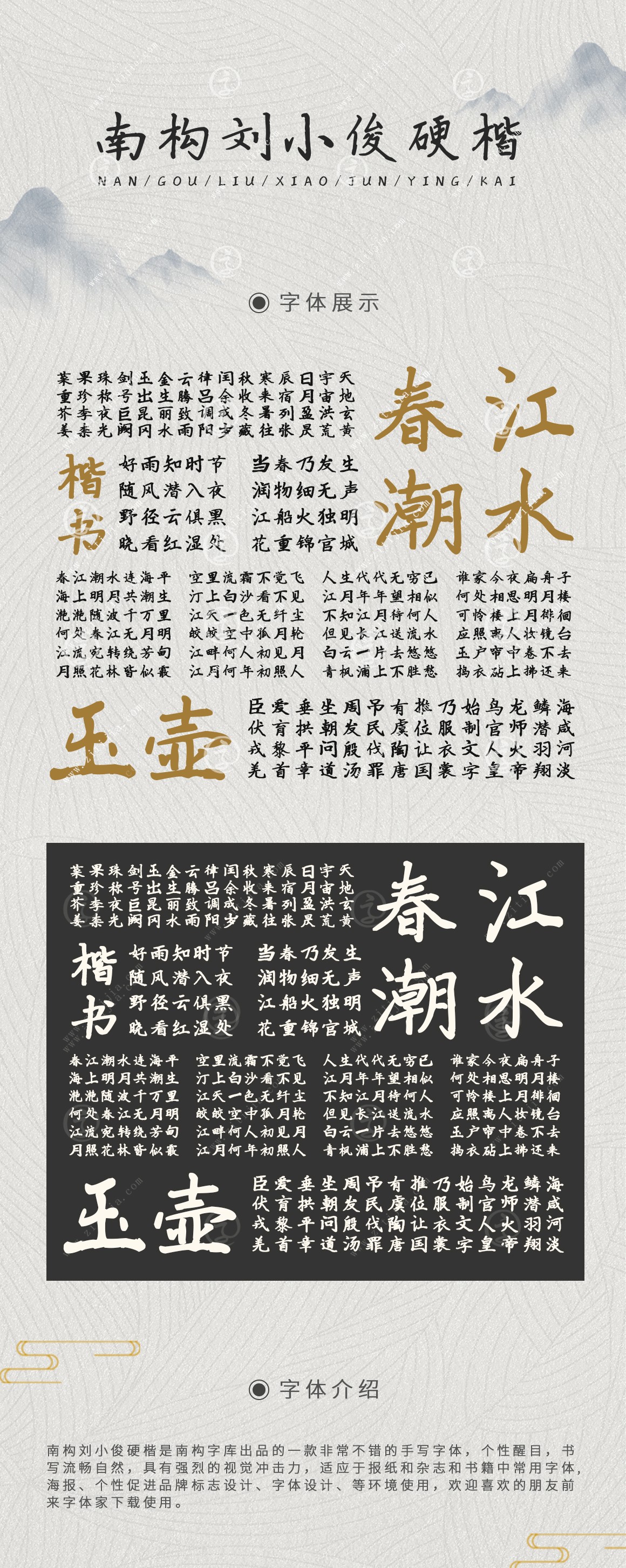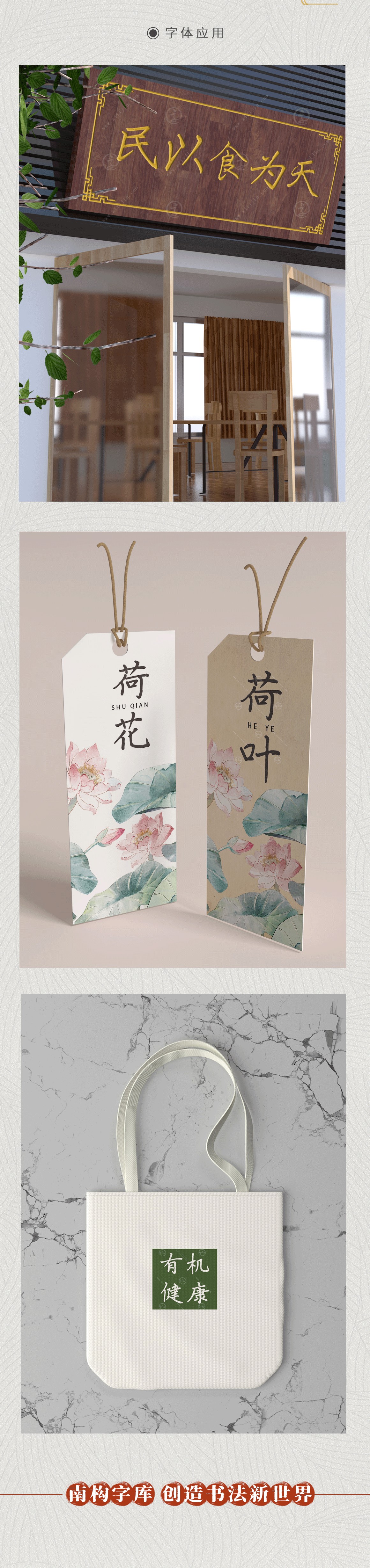
南構(gòu)劉小俊硬楷
南構(gòu)劉小俊硬楷是南構(gòu)字庫出品的一款非常不錯的手寫字體,個(gè)性醒目,書寫流暢自然,具有強(qiáng)烈的視覺沖擊力,適應(yīng)于報(bào)紙和雜志和書籍中常用字體, 海報(bào)、個(gè)性促進(jìn)品牌標(biāo)志設(shè)計(jì)、字體設(shè)計(jì)、等環(huán)境使用,歡迎喜歡的朋友前來字體家下載使用。